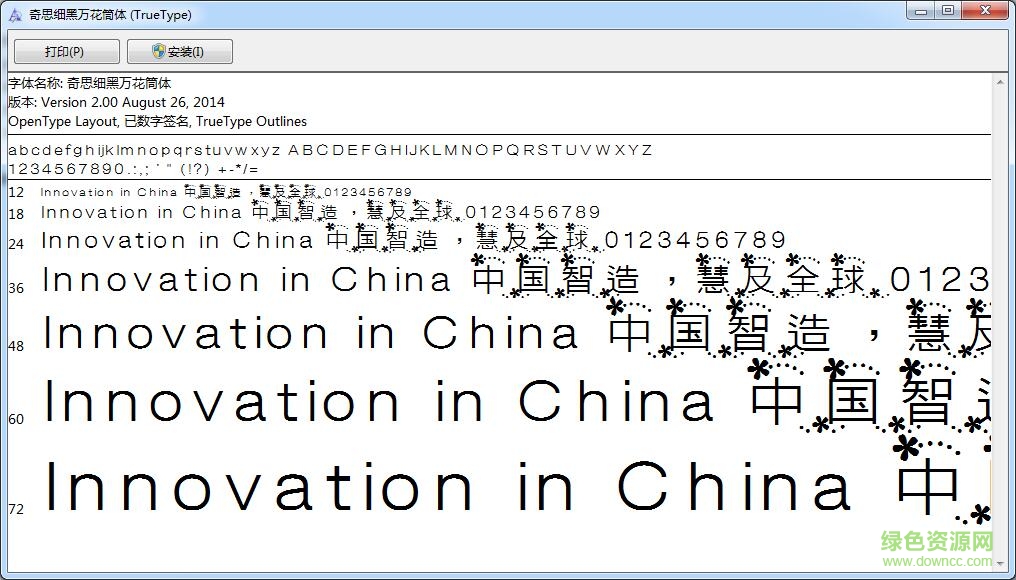
奇思細(xì)黑萬(wàn)花筒體是一款特別的黑體字體。這款字體外觀(guān)被花朵包圍,使字體看起來(lái)更加美觀(guān),可以用于美術(shù)設(shè)計(jì)、平面設(shè)計(jì)行業(yè)。支持多種電腦系統(tǒng)環(huán)境。需要的用戶(hù)可以來(lái)綠色資源網(wǎng)下載。